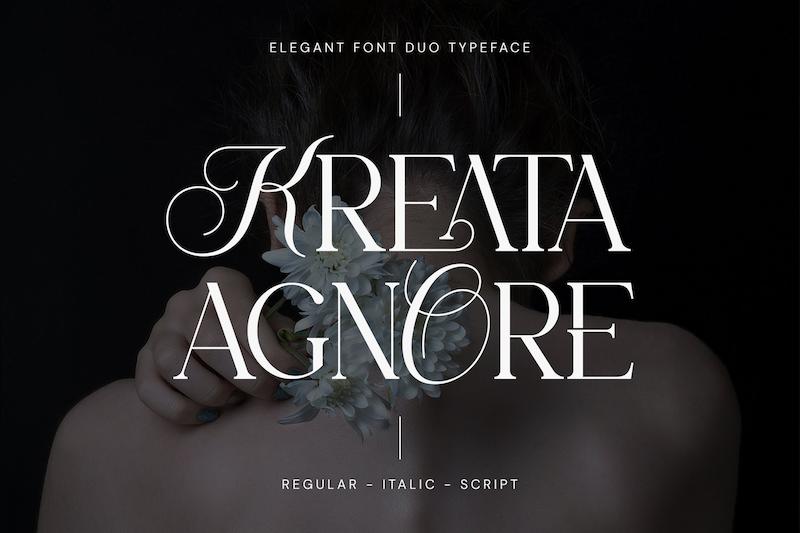
فونت انگلیسی کریتا آگنور (Kreata Agnore)
فونت دوگانه خوش‌استیل الگانت
کریتا آگنور یک تایپ‌فیس کاملاً جدید، منحصربه‌فرد، خوش‌استیل، شیک و مدرن است. این فونت‌ها شامل انواع رگولار یا معمولی، ایتالیک و اسکریپت سریف هستند که بهترین گزینه برای عناوین، لوگوها، برندسازی، مجلات، بسته‌بندی محصولات و دعوت‌نامه‌ها می‌باشند. پیچش‌ها و اتصال‌های شیک همراه با خطوط تمیز و منحنی‌های نرم، یک لمس فزاینده از کلاس را به هر پروژه‌ای اضافه می‌کنند. این فونت را به شریک کامل هر پروژه تبدیل کنید.
ویژگی‌های فونت کریتا آگنور:
• لیگچرهای چشم‌نواز
• حروف بزرگ و کوچک
• اعداد و علائم نگارشی
• طبقه‌بندی: دوگانه
• فاصله‌گذاری: نرمال
• اندازه بهینه: هر اندازه‌ای